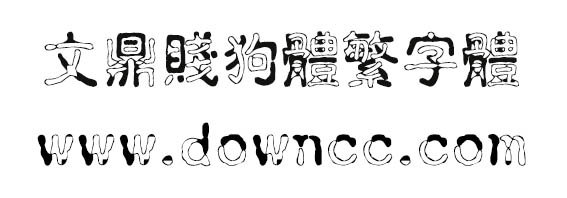
文鼎賤狗體繁是一款很有特色的繁體字體。為什么這么說(shuō)?因?yàn)樽煮w是空心實(shí)心相結(jié)合,部分筆畫(huà)空心,部分筆畫(huà)實(shí)心,很有特點(diǎn)。趕快到綠色資源網(wǎng)下載體驗(yàn)吧!
文鼎賤狗體繁就如名字一樣給人一種活潑靈動(dòng)的感覺(jué),字體整體帶有空心字的特點(diǎn),黑白填充交錯(cuò),給人一種不對(duì)稱美